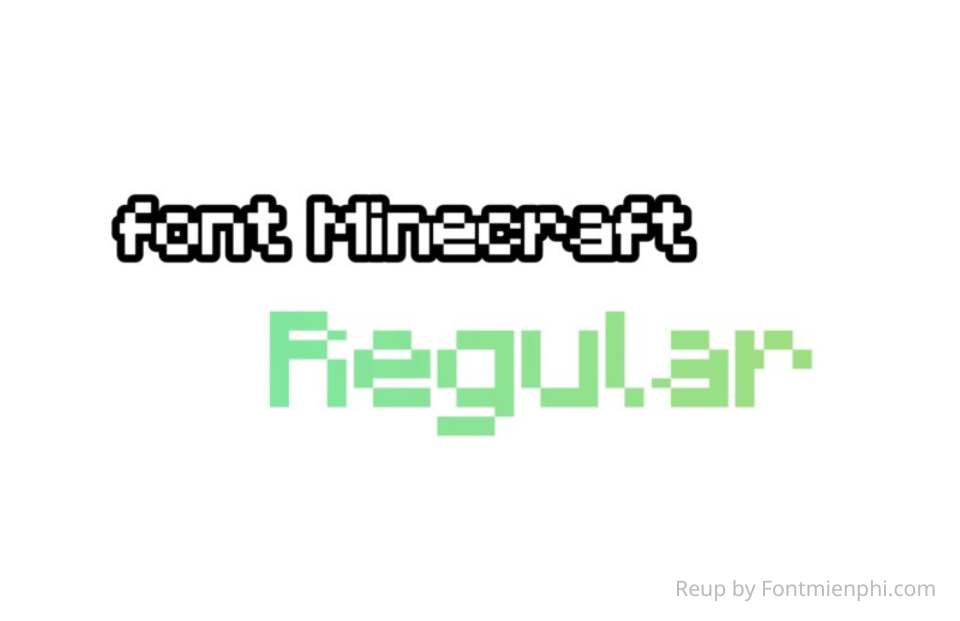
Tải Font Việt Hóa Minecraft Regular – Đậm Chất Đồ Họa Pixel Game
Minecraft không chỉ là một tựa game sinh tồn huyền thoại với hàng triệu người chơi trên toàn cầu, mà còn mang đến một phong cách thiết kế đồ họa 8-bit đặc trưng. Để đưa tinh thần này vào các thiết kế dành cho người Việt, Font việt hóa Minecraft regular chính là sự lựa chọn hoàn hảo nhất. Bài viết này sẽ giúp bạn hiểu rõ hơn về phông chữ độc đáo này và hướng dẫn tải bộ font miễn phí an toàn, nhanh chóng.
Font Minecraft Regular Là Gì?
Font Minecraft Regular là một kiểu chữ được thiết kế lấy cảm hứng trực tiếp từ những khối vuông (pixel) quen thuộc trong game. Với các đường nét vuông vức, góc cạnh, font chữ này tạo ra cảm giác hoài cổ (retro) nhưng vẫn giữ được sự ấn tượng, khỏe khoắn và hiện đại.
Tuy nhiên, bản gốc của phông chữ này do các nhà thiết kế nước ngoài phát triển thường không hỗ trợ đầy đủ các dấu câu trong bảng chữ cái tiếng Việt. Điều này dẫn đến tình trạng lỗi font, đứt nét hoặc sai định dạng khi gõ. Sự ra đời của phiên bản việt hóa đã giải quyết triệt để vấn đề này, mang lại trải nghiệm mượt mà cho các designer.
Tại Sao Thiết Kế Của Bạn Cần Font Việt Hóa Minecraft Regular?
1. Phong Cách Pixel Retro Độc Đáo
Mang đậm dấu ấn của đồ họa 8-bit cổ điển, phông chữ này có khả năng thu hút ánh nhìn ngay lập tức. Nó gợi nhớ về kỷ nguyên của những chiếc máy chơi game arcade, tạo sự phá cách, bụi bặm và nét cá tính mạnh mẽ cho bất kỳ ấn phẩm kỹ thuật số nào.
2. Tương Thích Hoàn Hảo Tiếng Việt
Nhờ quá trình tinh chỉnh và việt hóa kỹ lưỡng (kerning chuẩn xác), font chữ đảm bảo hiển thị cực kỳ sắc nét mọi dấu câu từ huyền, sắc, hỏi, ngã, cho đến dấu nặng. Bạn có thể tự do sáng tạo các tiêu đề nội dung tiếng Việt mà không lo bị lỗi hiển thị hay mất đi sự đồng bộ về mặt thẩm mỹ.
Ứng Dụng Linh Hoạt Trong Thiết Kế Đồ Họa Font Việt Hóa Minecraft Regular
Với vẻ ngoài đặc thù, Font việt hóa Minecraft regular phát huy sức mạnh tốt nhất khi được ứng dụng vào các dự án như:
Thiết kế banner, poster quảng cáo cho các sự kiện giải đấu eSports, gaming.
Làm ảnh thu nhỏ (thumbnail) trên YouTube, TikTok cho các streamer và nhà sáng tạo nội dung.
Thiết kế logo, áo thun (T-shirt) mang phong cách streetwear, geek hoặc văn hóa Pop.
Thiết kế giao diện website (UI/UX) hoặc ứng dụng điện thoại mang chủ đề retro cổ điển.